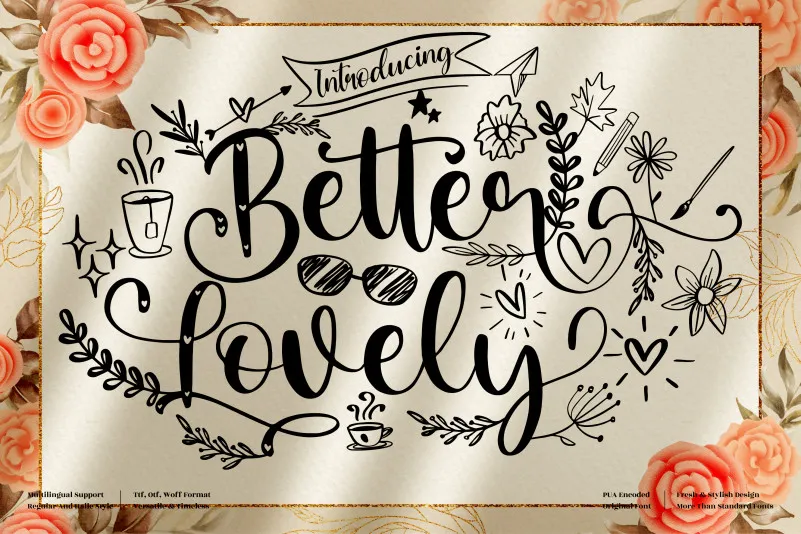
Better Lovely Font
A fonte ‘Better Lovely Font’ é perfeita para quem busca uma atmosfera encantada para seus projetos. Desenvolvida pelo designer perspectype, esta elegante e romântica fonte caiu de amor ao seu estilo. Ideal tanto para cartões de casamento, arte de estação, postagens interessantes em redes sociais quanto para qualquer outro projeto que deseje dar um toque especial. O PUA encoded garantindo que todos os caracteres e curvaturas sejam acessíveis com facilidade. Que tal transformar seus projetos digitais num maravilhoso convite de casamento, ou até mesmo na arte das cartas finas? Comece a desfrutar da ‘Better Lovely Font’ agora!